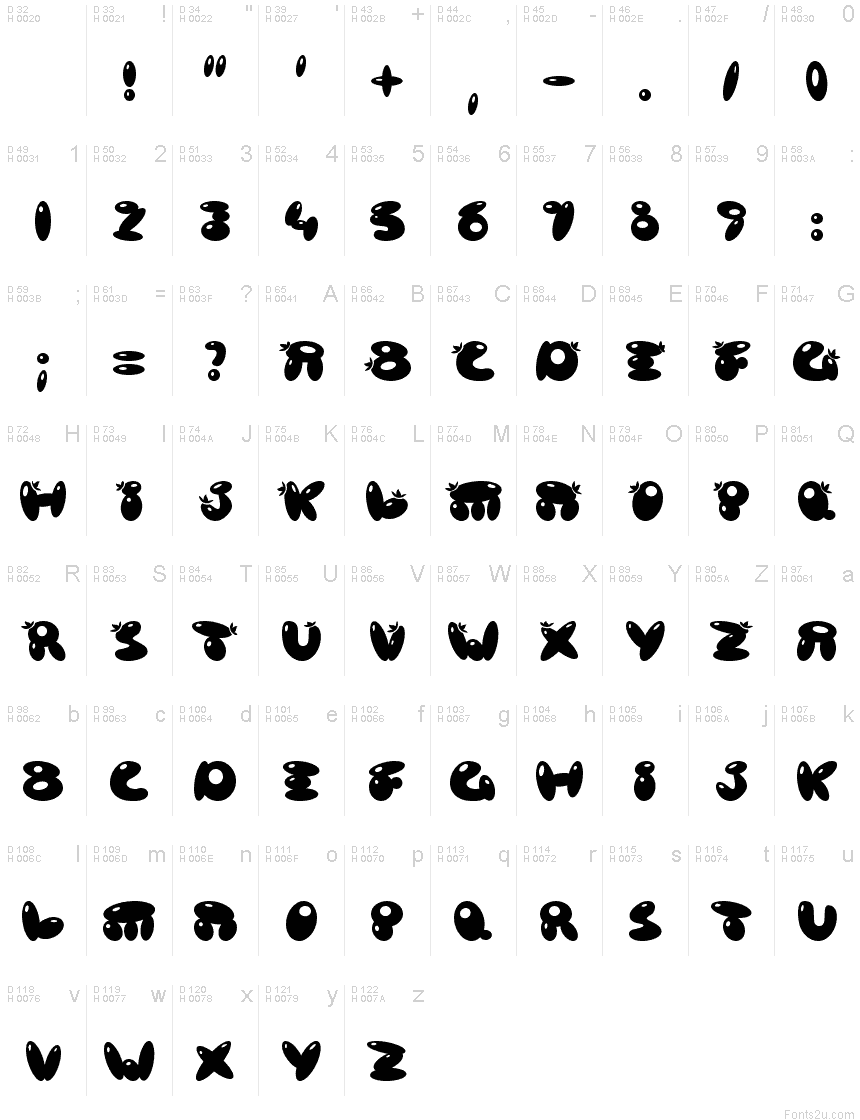
Poison Berries von Levi ist eine kostenlose Cartoon-Display-Schrift mit einem klebrigen, beerenartigen Alphabet und einem hinterhältigen Halloween-Grinsen. Die Buchstaben wirken geschwollen und glänzend, mit abgerundeten Buckeln, kleinen Bissspuren und hellen Glanzlichtern, die die Großbuchstaben wie klebrige Bonbons oder überreifes Obst aussehen lassen.
Damit ist sie die ideale Wahl für Party-Flyer, Kinderposter, gruselige Verpackungen, Comic-Titel oder verspielte Album-Artworks, bei denen die kostenlose Schrift die gesamte Stimmung trägt. Verwende sie für kurze Überschriften, Logo-Schriftzüge oder große Initialen, wenn die Buchstaben eher wie glänzende Blobs als wie geordnete Formen wirken sollen.